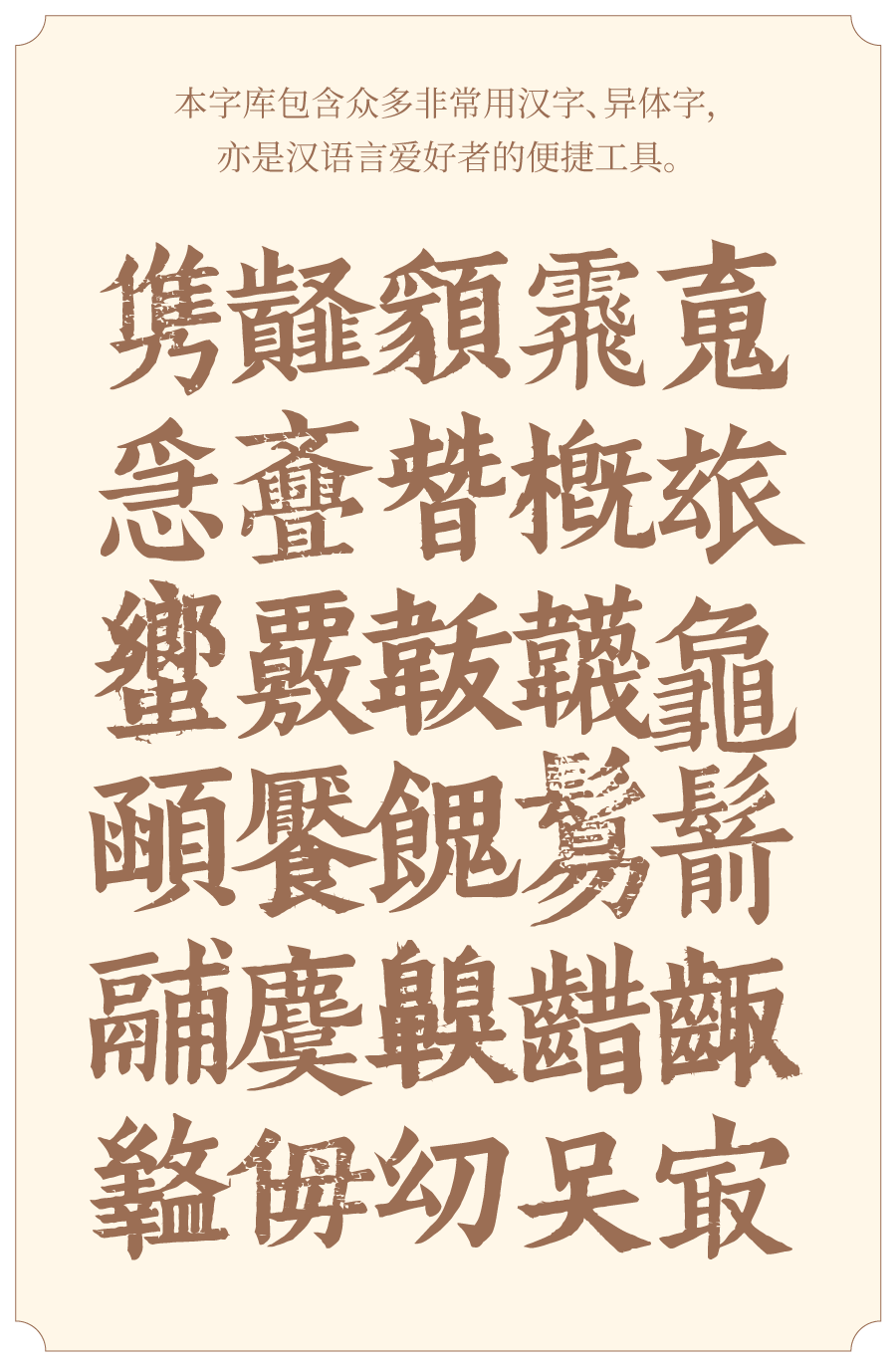
免费字体发布!——班马字类
《班马字类》是南宋娄机编撰的一部文字训诂学著作。全书共五卷,分为:平声上、平声下、上声、去声、入声。采录司马迁《史记》班固《汉书》所载古字、假借字,按四声编排,考证训诂,辨别音声,并对假借通用诸字罗列详备。
创客贴团队历时数月,将这本古代字典中包含的汉字开发成了现代电脑字库,采用Unicode编码,收录汉字1800余个。